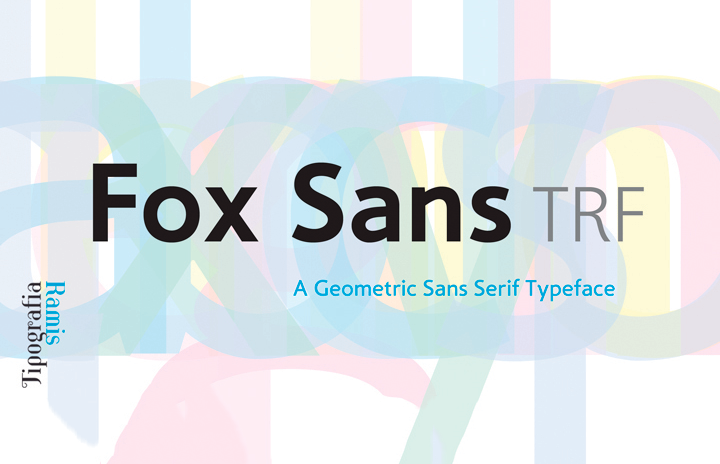
A Fox Sans TRF é uma nova adição à famosa familia de tipos Fox, criada pelo designer Tipoface e agora disponível no formato OpenType para download. A fonte Fox origem foi reformulada com foco na legibilidade, preservando sua originalidade, em um design neo-grotesco que não atrapalha com detalhes ornamentais. O novo subgrupo Fox Sans TRF incorpora seis estilos, ambos em códigos romanos e itálicos, sem distorções decorativas nos caracteres minúsculos. Esta fonte é recomendada para uso no estilo de texto, oferecendo uma variedade que não compromete sua simplicidade única. O Fox Sans TRF está disponível no formato de caractere do tipo Western CP1252, tornando-o versátil tanto em projetos digitais quanto impressos. Para designers e criativos, a Fox Sans TRF é um recurso visual que traz modernidade e facilidade na legibilidade para seus trabalhos.